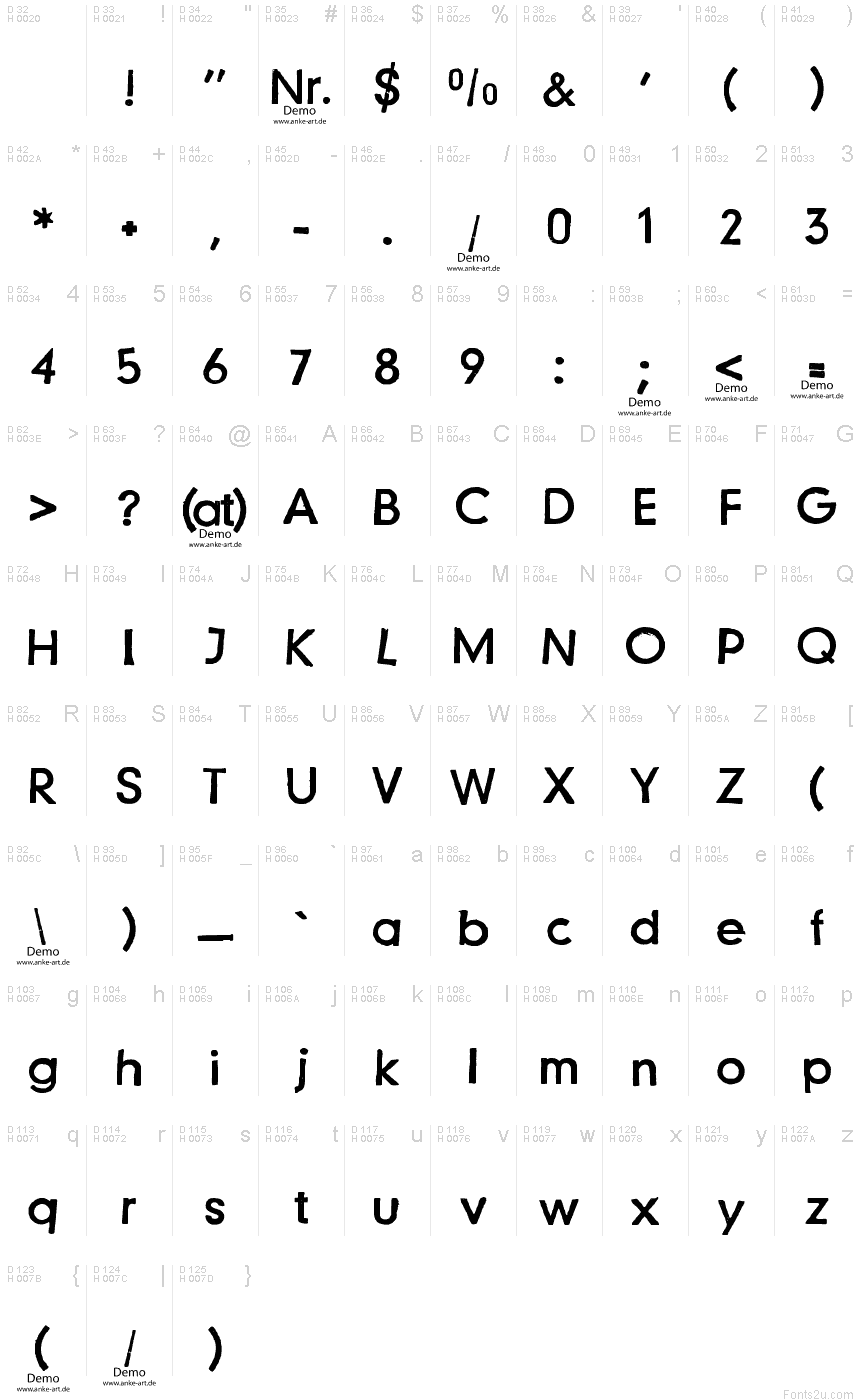
Just Another Stamp Font de Anke Arnold es una tipografía display gratuita de estilo sello con formas de letras gruesas e irregulares. Sus bordes suavemente desgastados y sus trazos desiguales imitan la tinta presionada sobre el papel, manteniendo al mismo tiempo un relleno interior sólido y claro. Las amplias curvas le aportan un peso agradable y artesanal.
Resulta especialmente convincente en el diseño de envases de alimentos, donde el efecto de impresión imperfecta sugiere productos artesanales de tirada reducida y etiquetas colocadas a mano. Estas mismas letras robustas se adaptan muy bien a carteles de eventos y artículos promocionales informales, sobre todo en ferias de artesanía, noches de comedia o tiendas independientes. En publicaciones infantiles y material escolar, su volumen redondeado puede formar parte de un letrero ilustrado o de una escena de papel recortado.